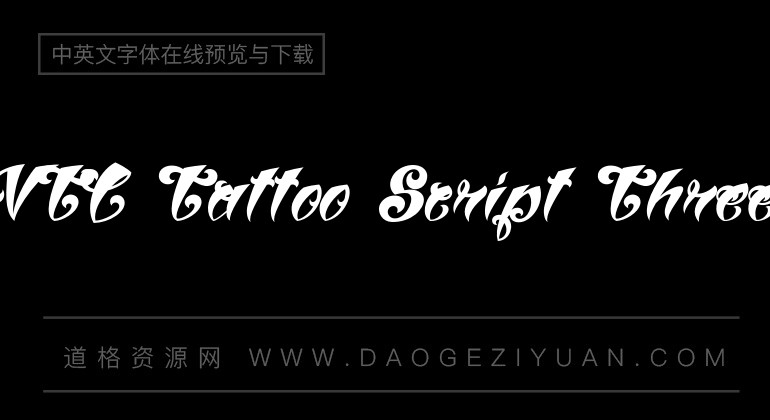
VTC Tattoo Script Three
VTC Tattoo Script Three 字体是一种手写风格的字体,专为纹身设计而创建。它由V.T.C. Vigilante Typeface Corporation开发,与其他纹身字体相比,它有着更加优美和流畅的曲线和线条。 该字体的风格具有很强的艺术感,包含了许多纹身中常见的图案和符号,如心形和骷髅头等。它的字母形状非常独特,让文字看起来更加生动和有趣。此外,它还包含了不同的字母间距和连字以增强艺术效果。 总的来说,VTC Tattoo Script Three 字体是一种特别设计用于纹身的字体,它具有独特的艺术感和美学价值,为纹身设计师和爱好者提供了一种创新和个性化的选择。
VTC Tattoo Script Three是一款非常不错的手写艺术字体,具有很好的视觉感,适合于文化类的宣传设计、商业类品牌的广告和产品包装设计以及个性化文字排版等较多场景。